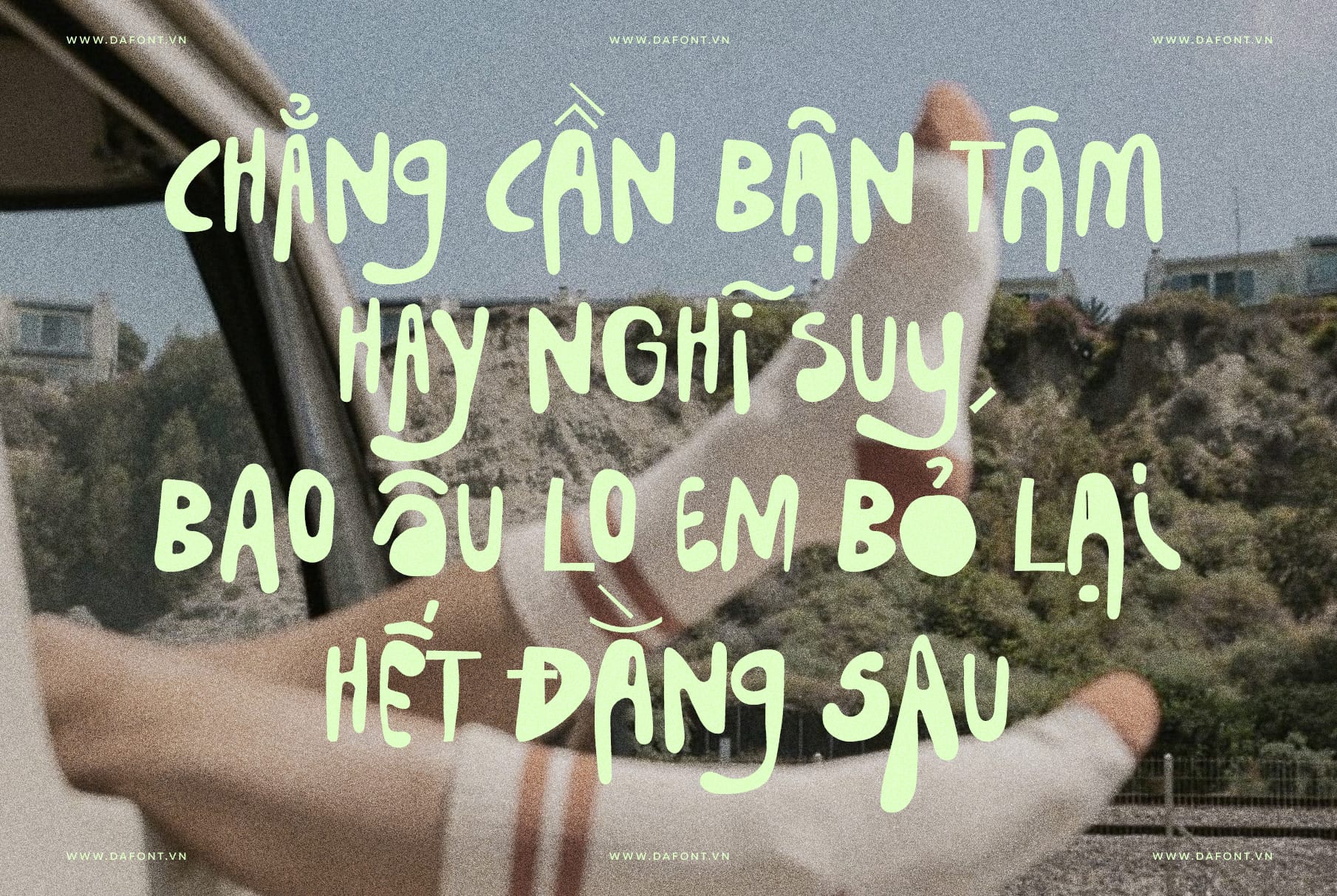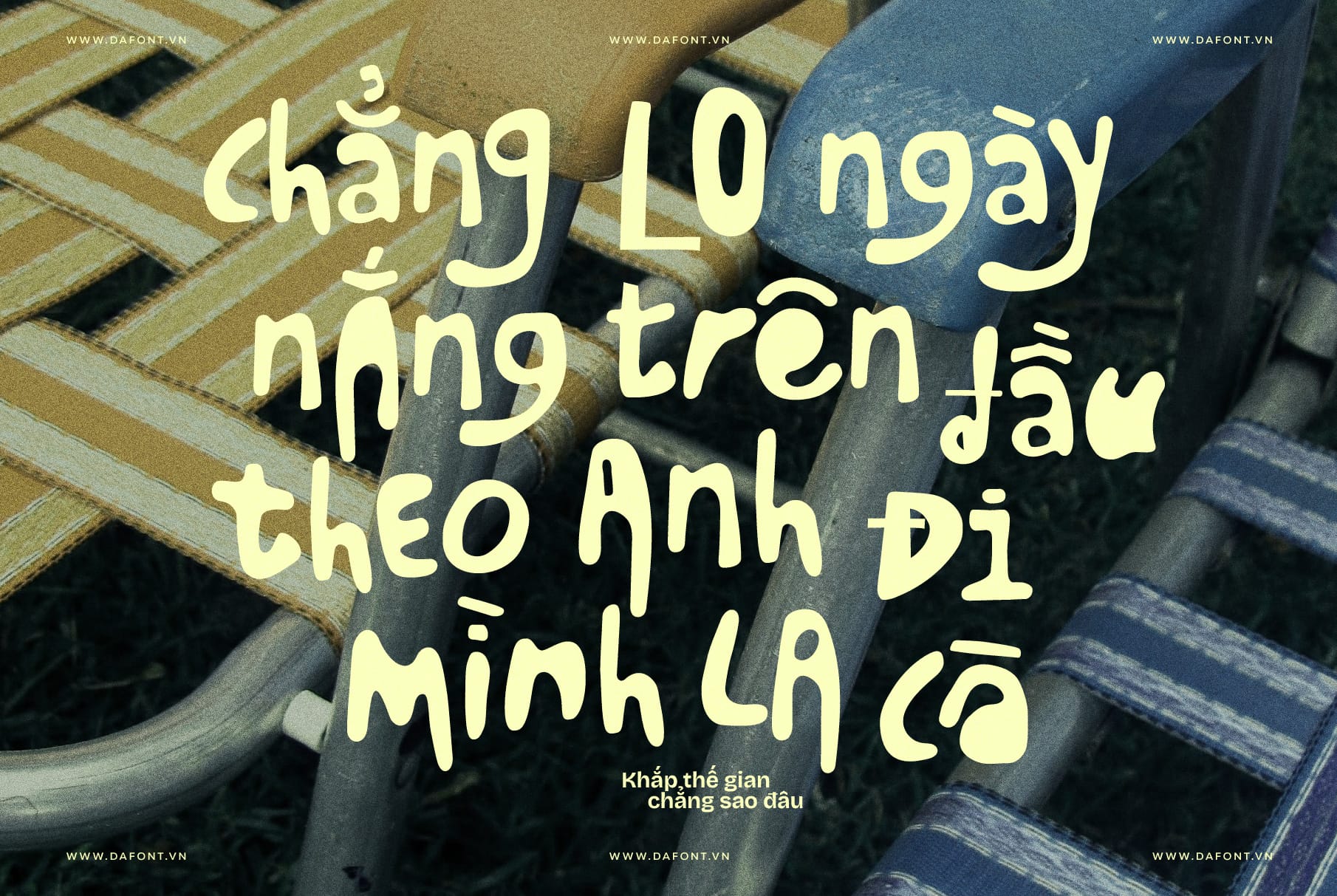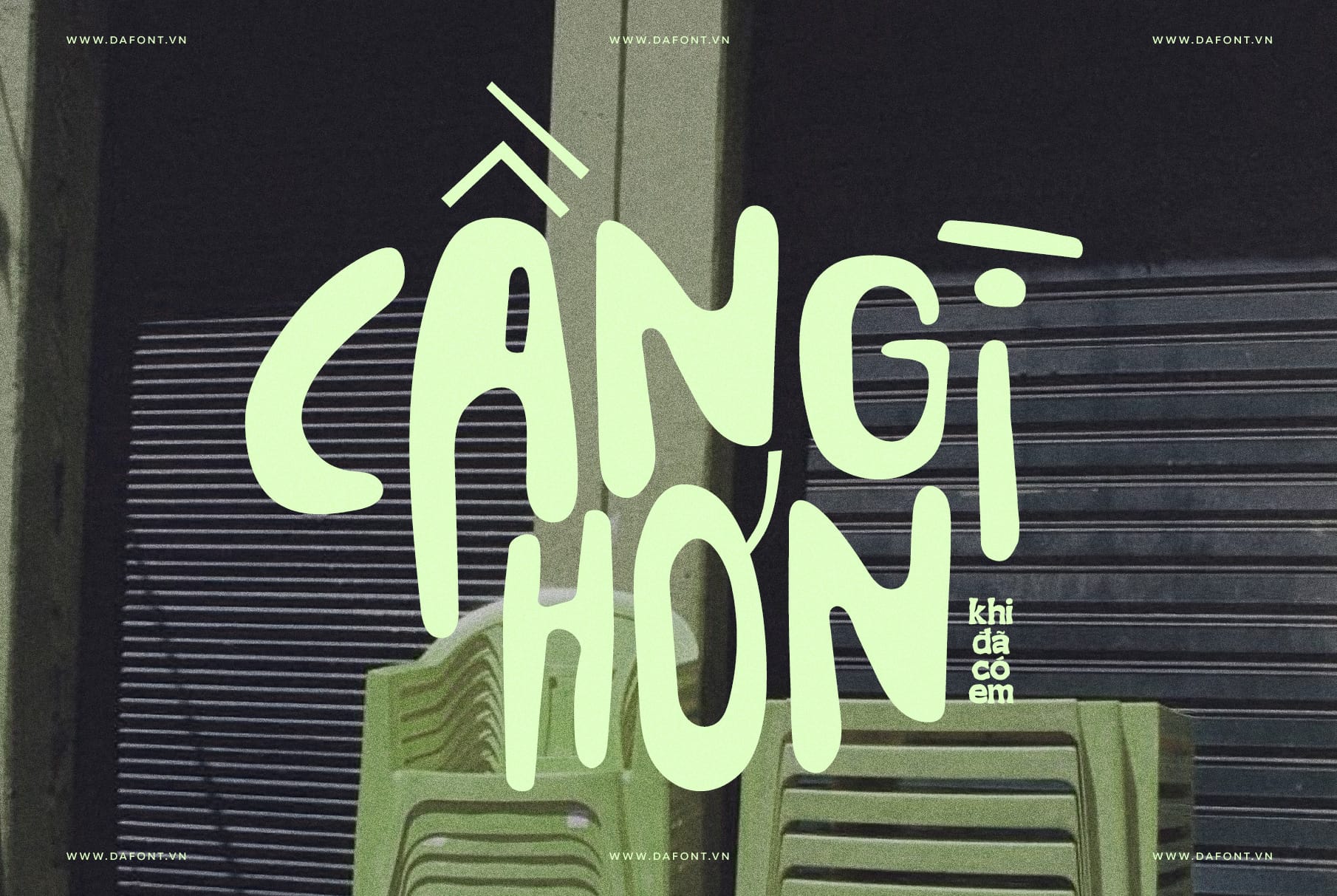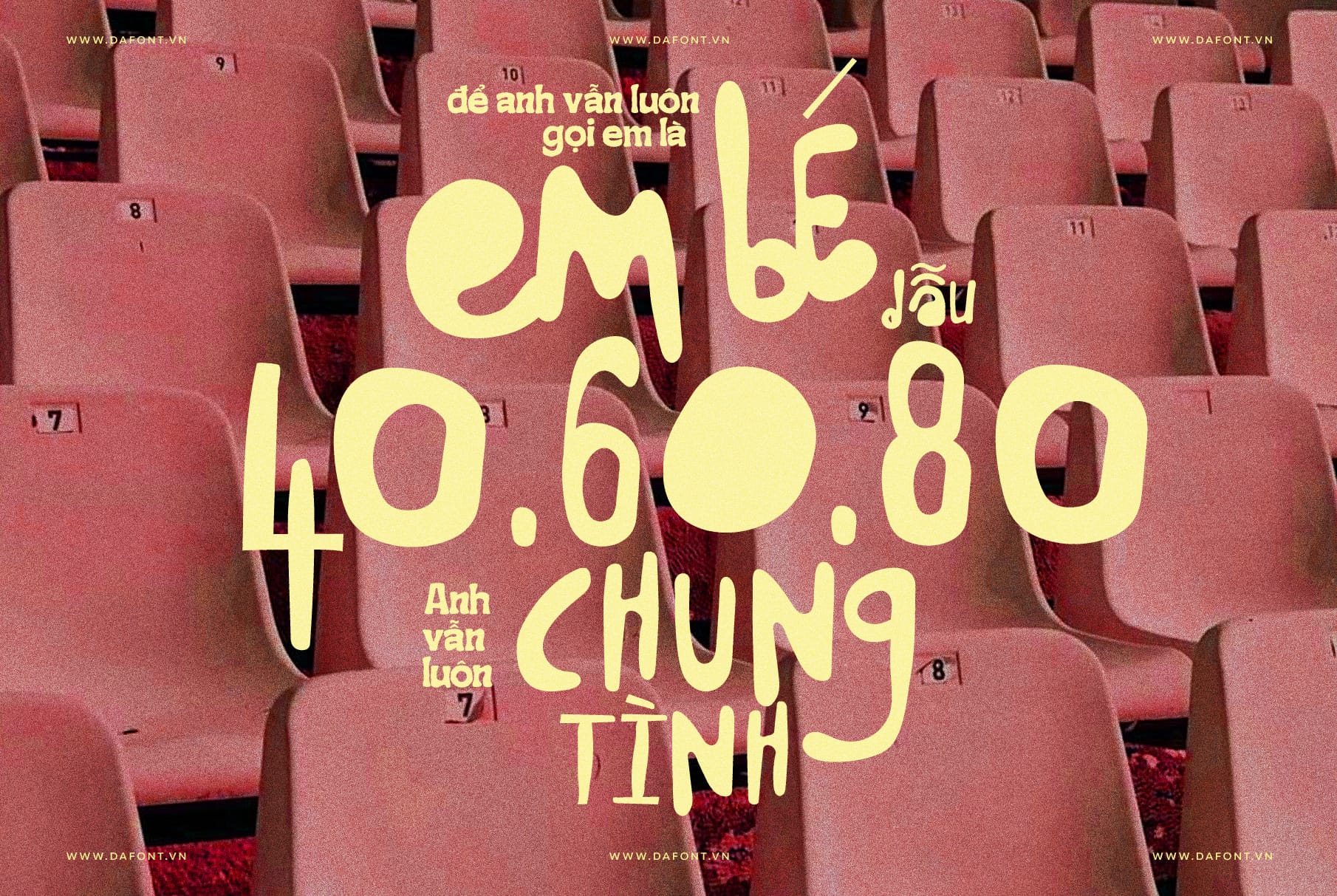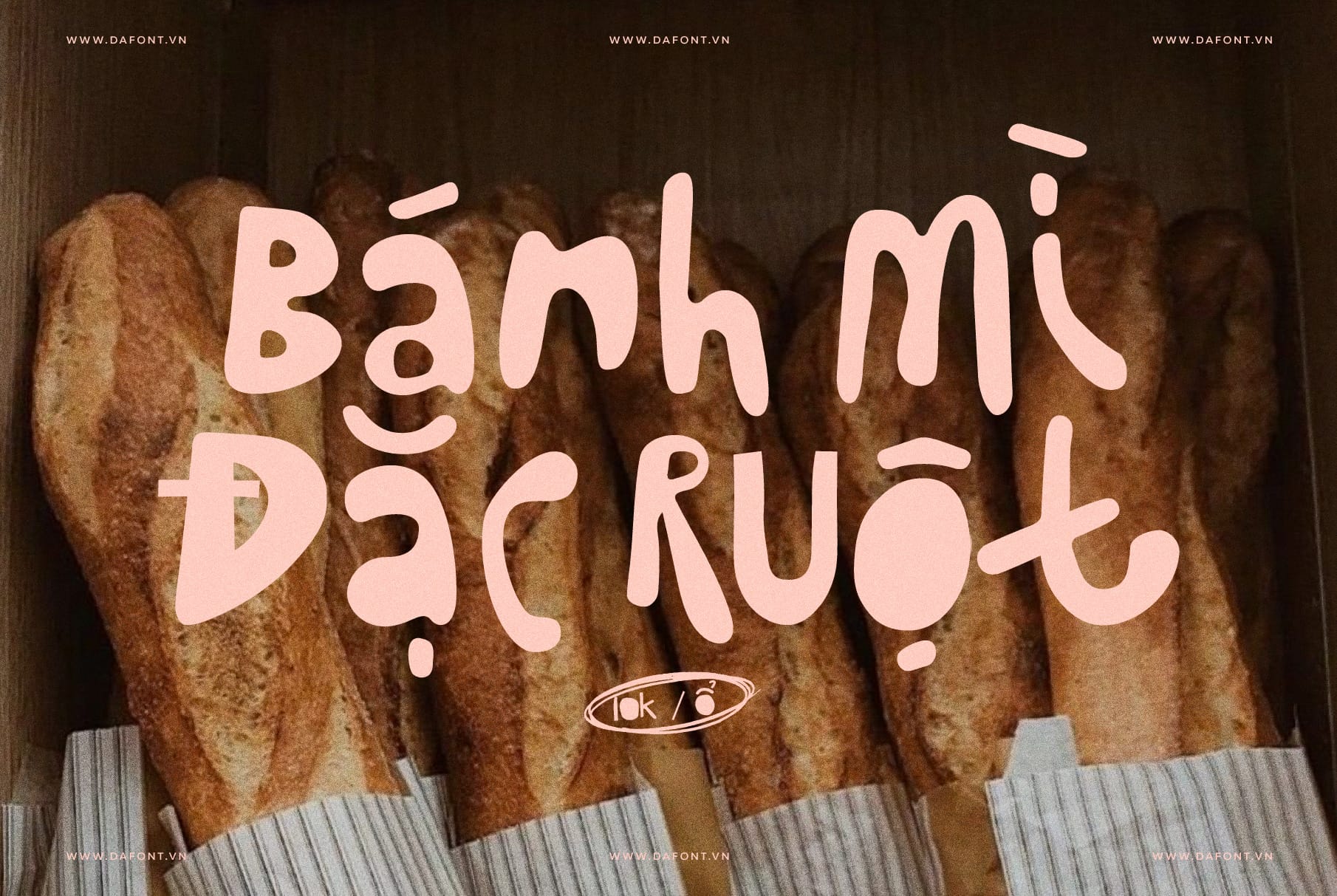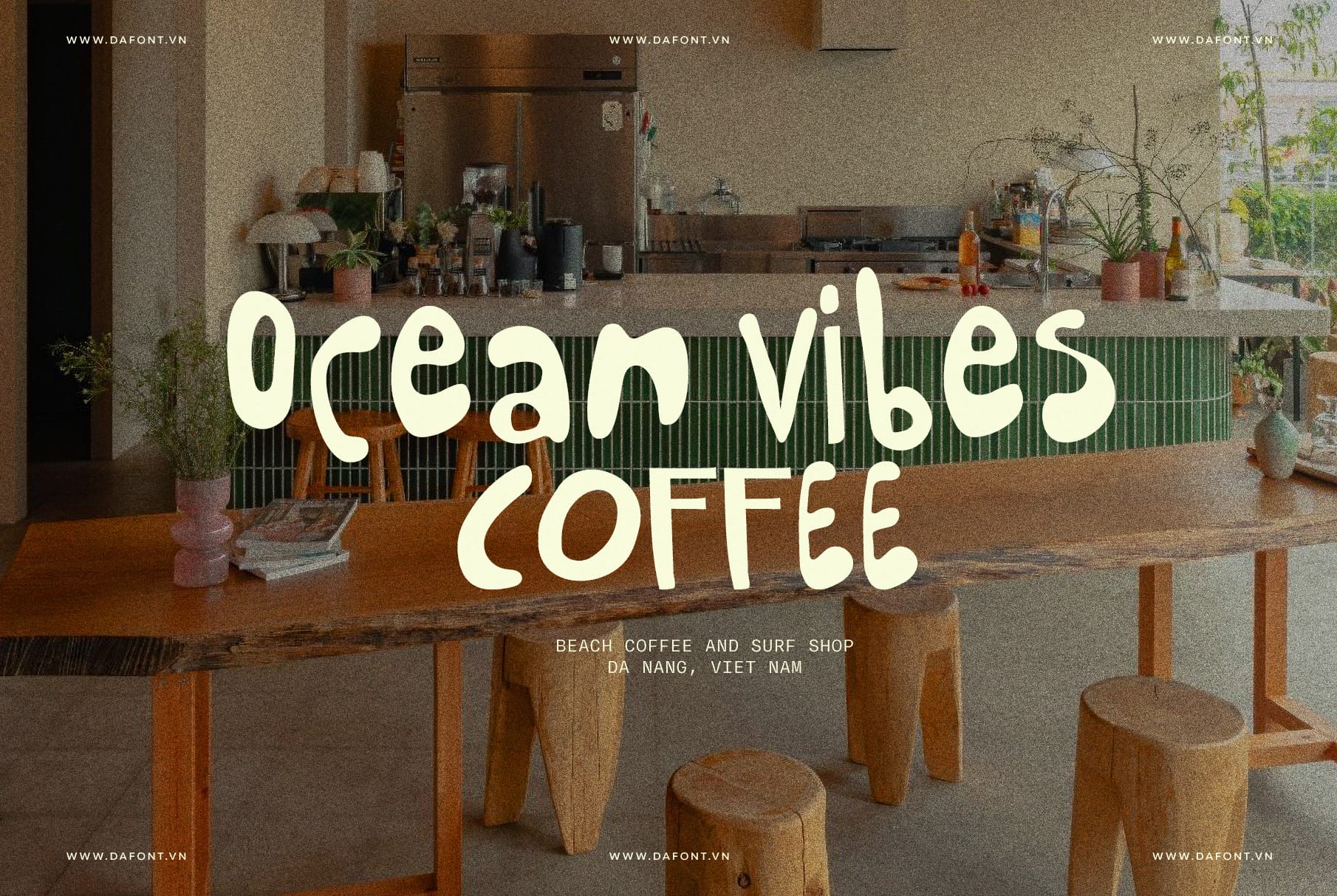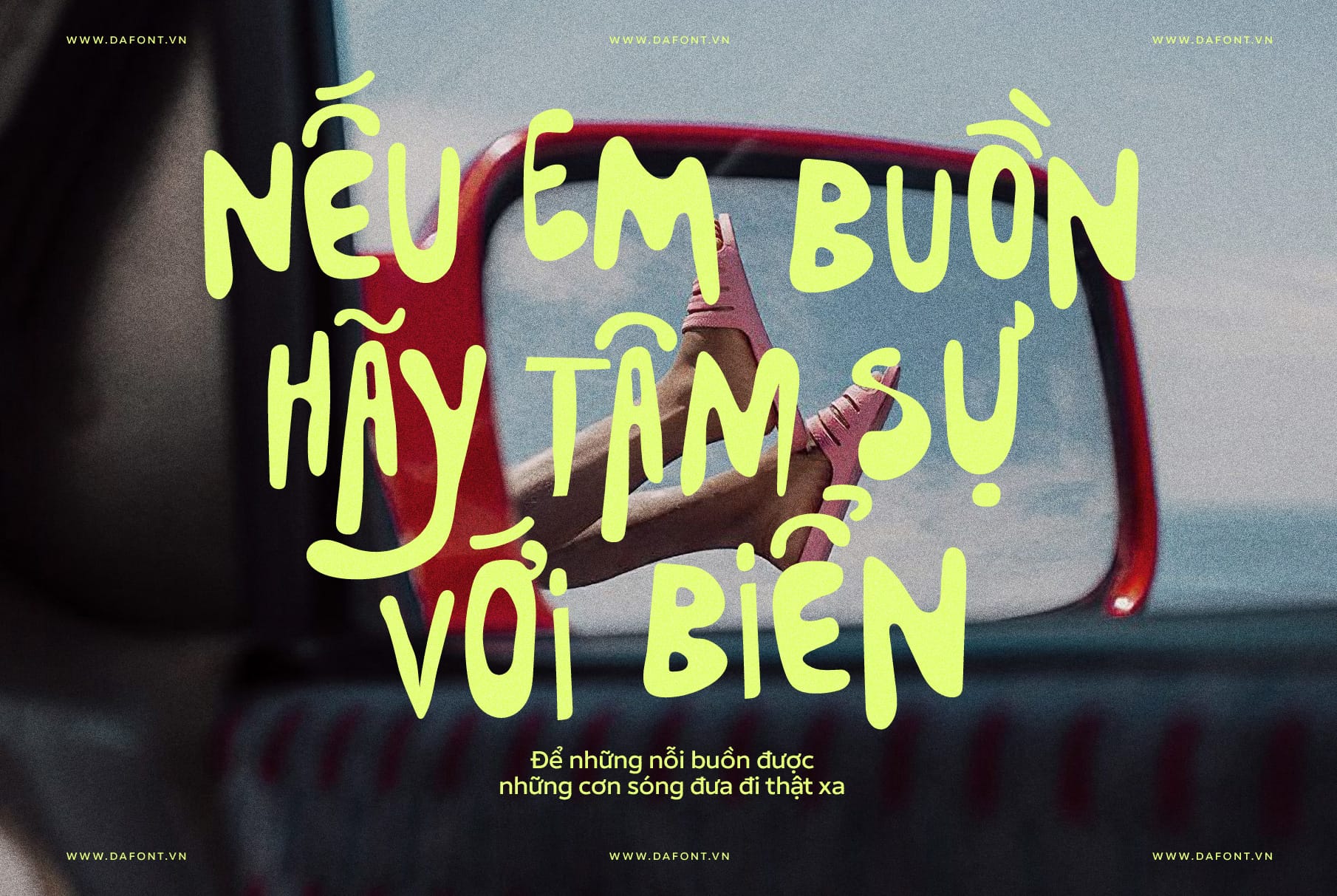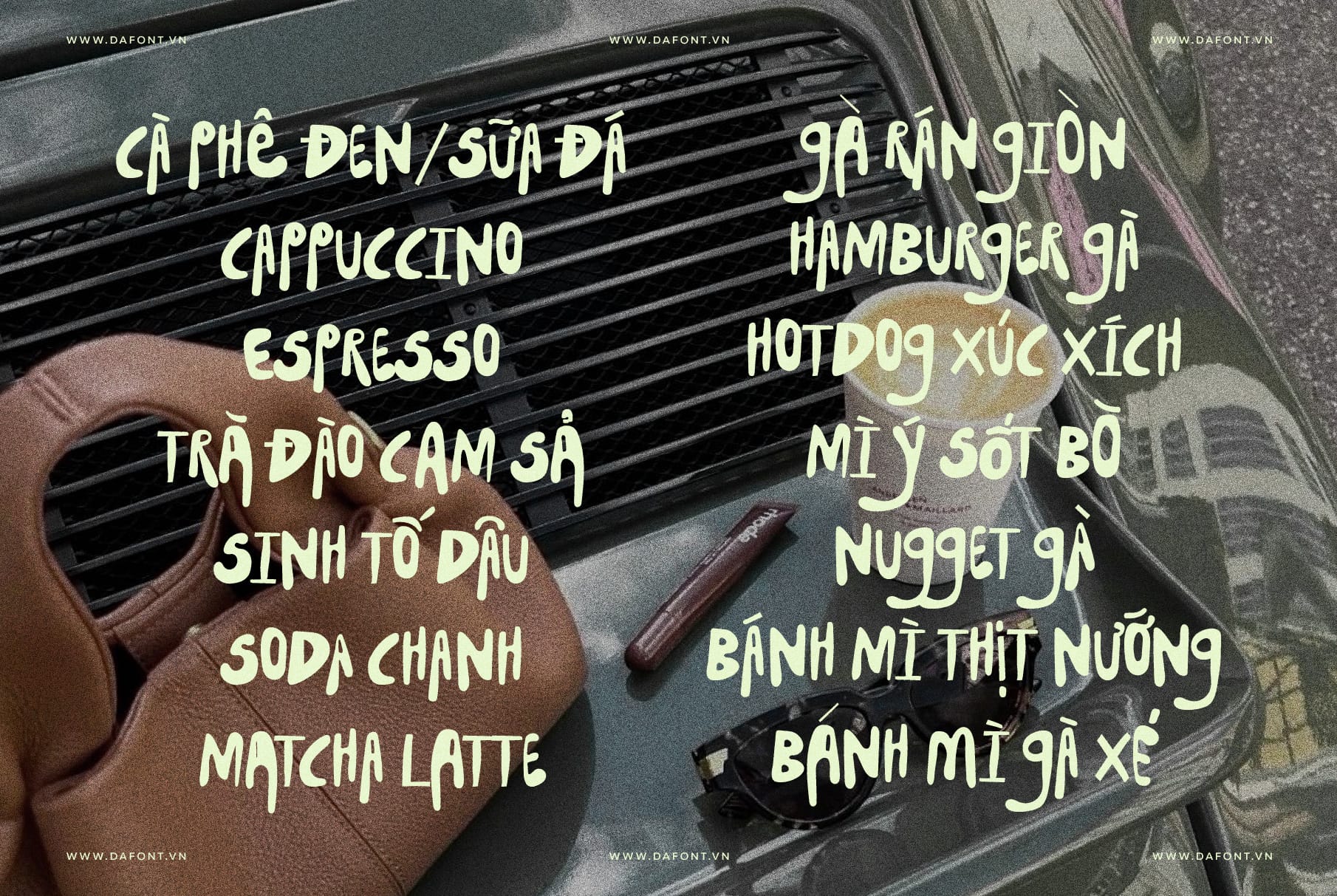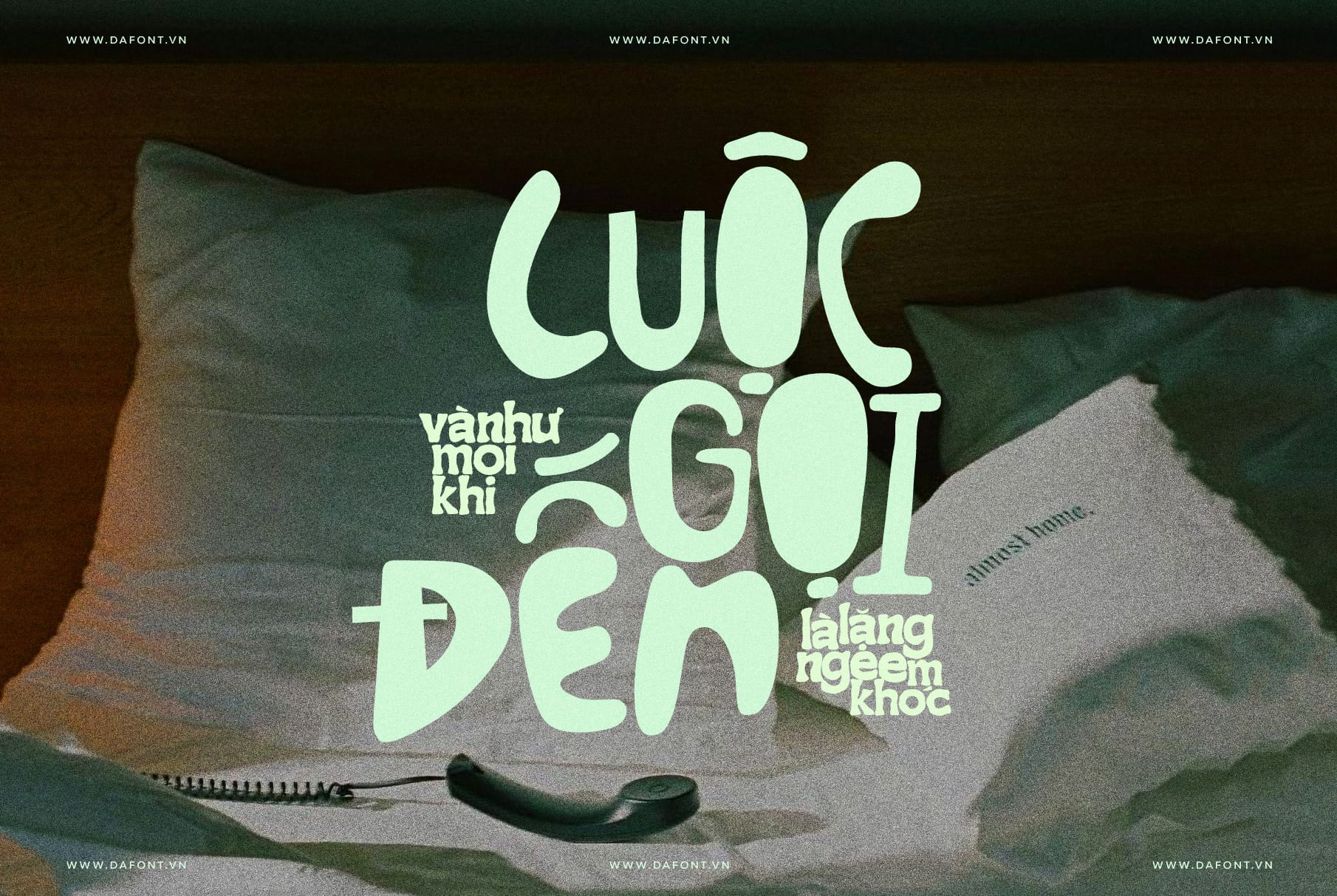
Bạn đang tìm kiếm một font chữ mang đậm chất tự do, phóng khoáng của biển cả? Bạn muốn thiết kế của mình toát lên vẻ đẹp hoài cổ (vintage) nhưng vẫn đầy cá tính? DFVN Bungalow font viết tay độc lạ chính là “làn gió biển” mát lành mà bạn đang tìm kiếm.
DFVN BUNGALOW là kiểu chữ viết tay, lấy cảm hứng từ vẻ đẹp của bờ biển Aotearoa (New Zealand) và văn hóa lướt sóng ở California những năm 1970. Được “sinh ra” từ nhịp sóng biển và những nét bút tự do, mộc mạc ở Whangamatā – một trong những thiên đường lướt sóng được yêu thích nhất tại New Zealand.
Ban đầu, BUNGALOW được tạo ra dành riêng cho một nghệ nhân làm ván lướt sóng, mở rộng từ logo vẽ tay của họ thành một bộ kiểu chữ đầy cá tính. Mỗi chữ cái đều thiết kế ngẫu nhiên với những nét chữ độc đáo, mô phỏng cảm giác thủ công của ván lướt sóng làm tay, biển hiệu vẽ tay và những căn nhà gỗ ven biển cổ điển. Không thẳng tắp, không cứng nhắc – mà mềm mại, tự nhiên và đầy sự tự do.
Hãy sử dụng BUNGALOW khi bạn muốn mang lại tông màu thư thái, hoài cổ cho thương hiệu, thời trang, thiết kế poster, ấn phẩm, thumbnail nổi bật mạng xã hội (Tiktok, Facebook, Youtube..) hoặc bất kỳ dự án sáng tạo nào cần một vẻ đẹp nắng gió, mặn mòi và giàu cảm xúc của biển cả.
DFVN Bungalow - Việt hóa xịn sò
Phiên bản Việt hóa chất lượng, toàn bộ ký tự được xử lý tỉ mỉ để đảm bảo cân đối, rõ ràng và đồng nhất khi sử dụng trên mọi thiết kế.
• Thiết kế thêm bộ chữ thường mềm mại, rất hợp style viết tay
• Thiết kế thêm hơn 100 ký tự độc đáo
• Vẽ lại dấu tiếng Việt theo kiểu ngẫu hứng, sống động, không bị cứng
• Kerning toàn bộ ký tự để font nhìn phóng khoáng hơn không bị gò bó
• Tối ưu lại toàn bộ ký tự để dùng mượt mà hơn
• Update thêm 300+ ký tự thay thế siuuu độc đáo
• Tính năng Opentype được hỗ trợ
Mẹo sử dụng Bungalow (DFVN) trong thiết kế để thu hút hơn
Dùng cho tiêu đề, logo và điểm nhấn: Bungalow là display font - hãy ưu tiên dùng cho headline, tagline hoặc logo. Với đoạn văn dài, kết hợp thêm một font serif/sans dễ đọc để giữ trải nghiệm người dùng.
Kết hợp với ảnh film, grain và texture giấy: Font sẽ nổi bật khi đặt trên nền ảnh biển, bầu trời hoặc giấy có texture/film grain, giúp tăng chiều sâu và cảm giác vintage.
Chọn bảng màu phù hợp: Ưu tiên tông màu ấm: kem, vàng nắng, xanh olive, nâu nhạt… Những màu này kiểu phong cách vibe retro 70s và làm chữ trông ấm áp, mộc mạc.
Tối ưu khoảng cách chữ & dòng: Nới nhẹ tracking và tăng line-height để chữ “dễ thở” hơn; khiến cho là tổng thể hài hòa, tạo cảm giác thư thái đặc trưng của seaside lifestyle.
Đảm bảo contrast khi dùng trên social: Sử dụng font DFVN Bungalow trên nền đơn giản, tránh nền quá rối. Nếu cần, thêm outline hoặc shadow mờ để đảm bảo đọc rõ trên màn hình di động.
Mang nắng - gió - cát và vẻ đẹp của biển vào thiết kế của bạn
DFVN Bungalow một kiểu chữ đầy cảm xúc, giúp thiết kế của bạn trở nên sống động và giàu cá tính hơn. Với nét viết tay phóng khoáng, cấu trúc chữ mềm mại, font dễ dàng hòa hợp với nhiều phong cách sáng tạo - từ branding, poster, packaging đến social media. Đây là lựa chọn lý tưởng cho những dự án cần sự độc đáo, tự nhiên và khác biệt mà vẫn đảm bảo tính thẩm mỹ.